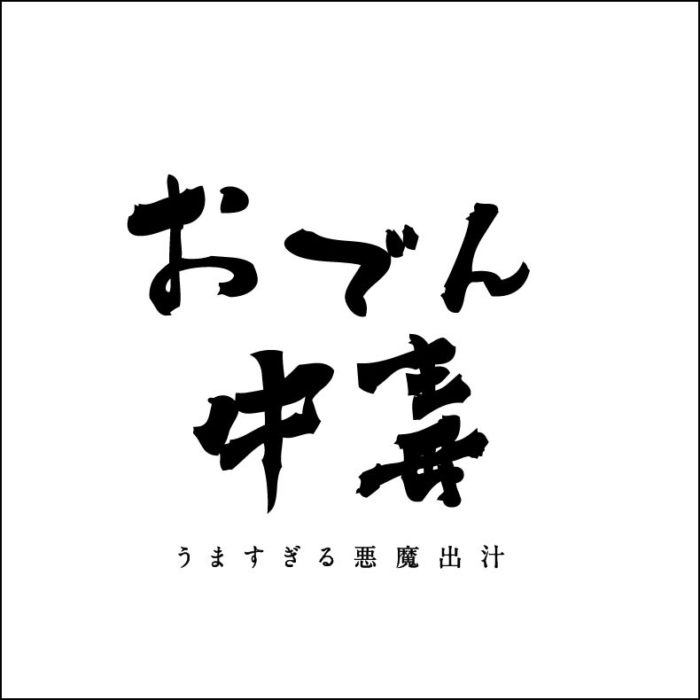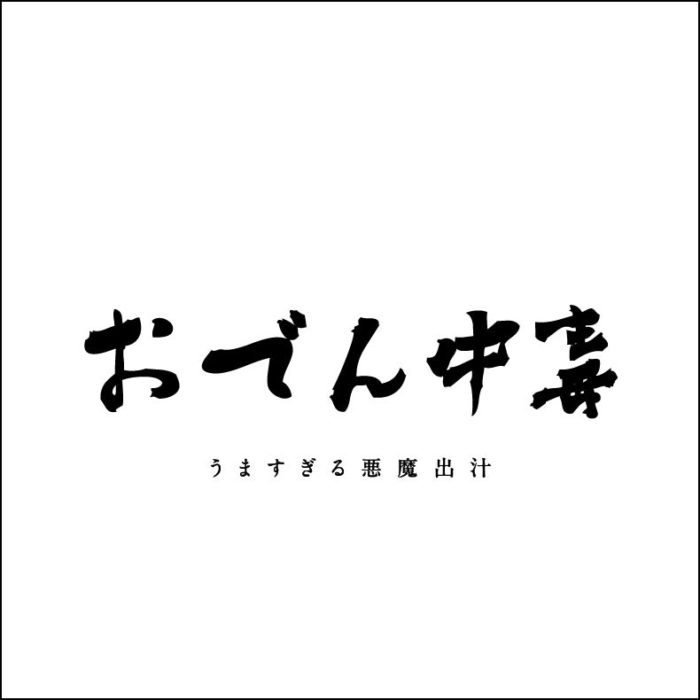
僕は日々デザインを作るときのフォントを選びにかなりこだわりがあります。(デザイナーは大抵ありますね…)
でもデザインを仕事にしていない人は「フォント選びをする、それ以前にフォントを持っていない」という現実があることに最近気づきました
もちろんフォントの種類を持っていなくても、上手にできるデザインジャンルはあるのですが、様々な種類のフォントを持っている方が簡単に高品質なデザインが作れることも多いです。
今回は個性的なフォントセットを販売しているデザインカッツさんのセールに合わせ個性的なフォントを事例付きで紹介します。
ちなみに僕が思う「いいデザインを作るために必要なフォント」とは…
僕がデザイナーを始めたい人に「いいデザインを作るために必要なフォントはなにをそろえればいいですか?」と質問をされたこう答えます。
1.明朝、ゴシックの基本フォント(太さをたくさん揃える)
2.雰囲気のあるデザインフォント
最初は良質なゴシックと明朝、そしてその他個性的なフォントたちがいくつかあればなんとかなると思っています。
昔はデザインフォントなんてあまりなかったので、デザインごとに自作していることも多かったですが、今は良質な有料フォントがありますので頼って時短することをおすすめします。
DESIGNCUTS のおすすめフォントセット
というわけで、今回はDESIGNCUTSというサイトで売っているおすすめフォントを事例とともに紹介します
デザインカッツさんでは上の画像のように、フォントが10個くらい入ったフォントパックみたいなものが格安で売っています。
さて、現在セール中のデザインカッツさんのフォントセットの中からおすすめフォントをオリジナルの事例とともに紹介します!
たくさんあるフォントセットの中から最初に気になったのはこのフォントセットです。
これめちゃくちゃいいフォントあると思うんですがどうですか?
楽しい!個性派日本語フォント集(10フォント入ってる)
楽しい!個性派日本語フォント集には10このフォントが入っています
この中で、最初にいいなと思ったのが三丁目明朝です
公式サイトにはこんな事例があります
三丁目明朝事例
いい感じですね。
ただ、これを普通にフォントで打つとこんな感じ
悪くないけど、ちょっとホラー的なイメージもあるかもしれませんね。
ただ、これを少しだけ太くして斜めにしたりすると…
結構良さそうじゃない?
太さでパワーが出たし、個性のある文字になりました
タイトルなどにも使えそう!
というわけで、デザインに当てはめてみたのがこちらです。
どうですか?
尖った感じでかっこいい広告が作れた気がします。
侍って感じがしたので勝手に侍キャンペーンにしました
ちなみに上のAmazon〜部分もこのフォントです。
※フォントのアウトライン線だけにしてる
注意
これも悪くないけど、ちょっとホラー感や手書き線の感じが悪い方向に出ている気がする。使い方によってはこういうイメージになるので注意です
ホラーっぽくすると…
ホラーもかなりイメージに合ってるね…
そしてこのセットから、もう一ついいなと思ったフォントを紹介します
それは…
奇妙フォント
フォント名が奇妙って…
と思ってみるとこんな感じ、高いお酒っぽいじゃないですか
僕も作ってみました
まずはカツ丼屋さんのロゴとか…
おでんやのロゴとか…
つまりこのフォントは奇妙なフォントというより「おいしそうなフォント」なんじゃないかと思うんです。
たまに高い店とか、こだわりのラーメン屋とかこういうフォントのお店ありません?
そういう味のあるおいしく見えるフォント、それが奇妙かと思いました
⬇こういうフォントで作られたラーメン屋さんあるよな〜
デザインカッツさんの楽しい!個性派日本語フォント集の紹介でした
2つのフォントの使い方を説明していきました
その他8つのフォントも使えるものもあると思います。